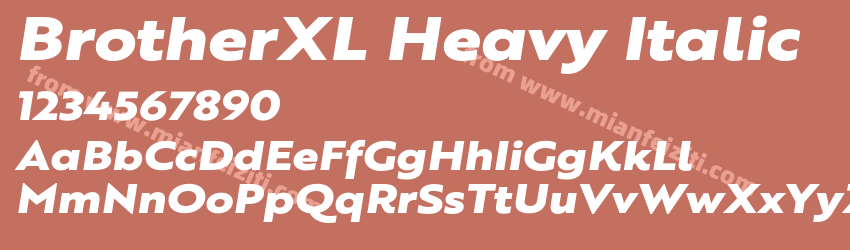
BrotherXL Heavy Italic
字体名称: BrotherXL Heavy Italic
Postscript名称: BrotherXL-HeavyItalic
字体字重: Heavy Italic
本款“BrotherXL Heavy Italic”是一款书写很新颖的字体,字体大方,适合各种设计作品使用!欢迎下载!